卡通字体大全让世界瞬间成为卡通乐园
随着市场经济的快速发展,产品的竞争力是企业立于不败之地的支撑,而设计却是提升产品整体效果,打造特色品牌的必备之选。然而在整个创意设计过程中少不了字体大全,通过独特新颖的设计能够充分展现产品的特性和传达的意蕴,从而凸显设计目标,当然在一个完美的设计中需要融合多种元素,通过元素的合力搭配才能得到意想不到的收获,而字体就是这些元素当中关键的一种。
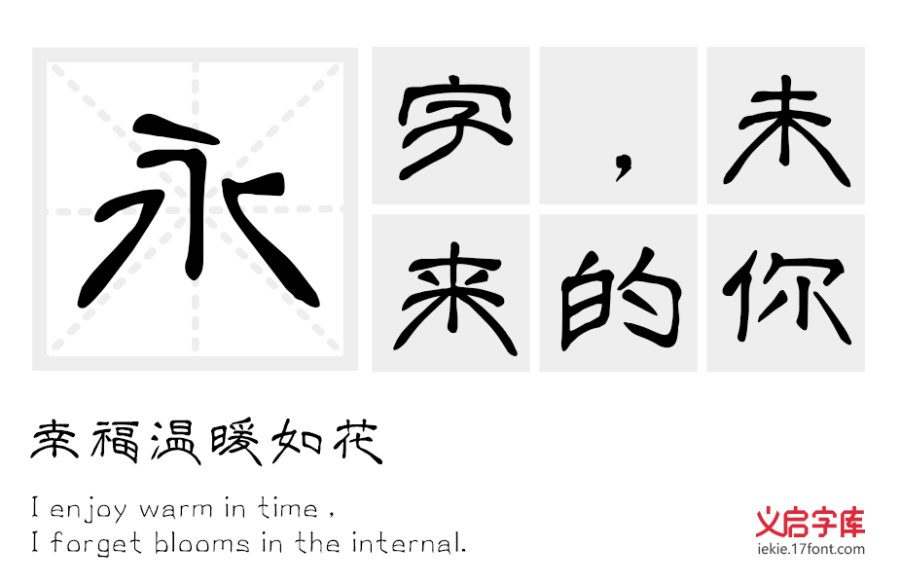
义启字库推出的字体大全里面有很多是适合现今比较流行且应用范围极为广的卡通可爱字体,卡通字体的种类繁多,极大的满足了人们对不同字体的实际需求,卡通字体能有效融合进设计环境,比常用的普通字体更有表现力,从而提升了产品的设计效果,也让更为烦琐的设计变得易如反掌。